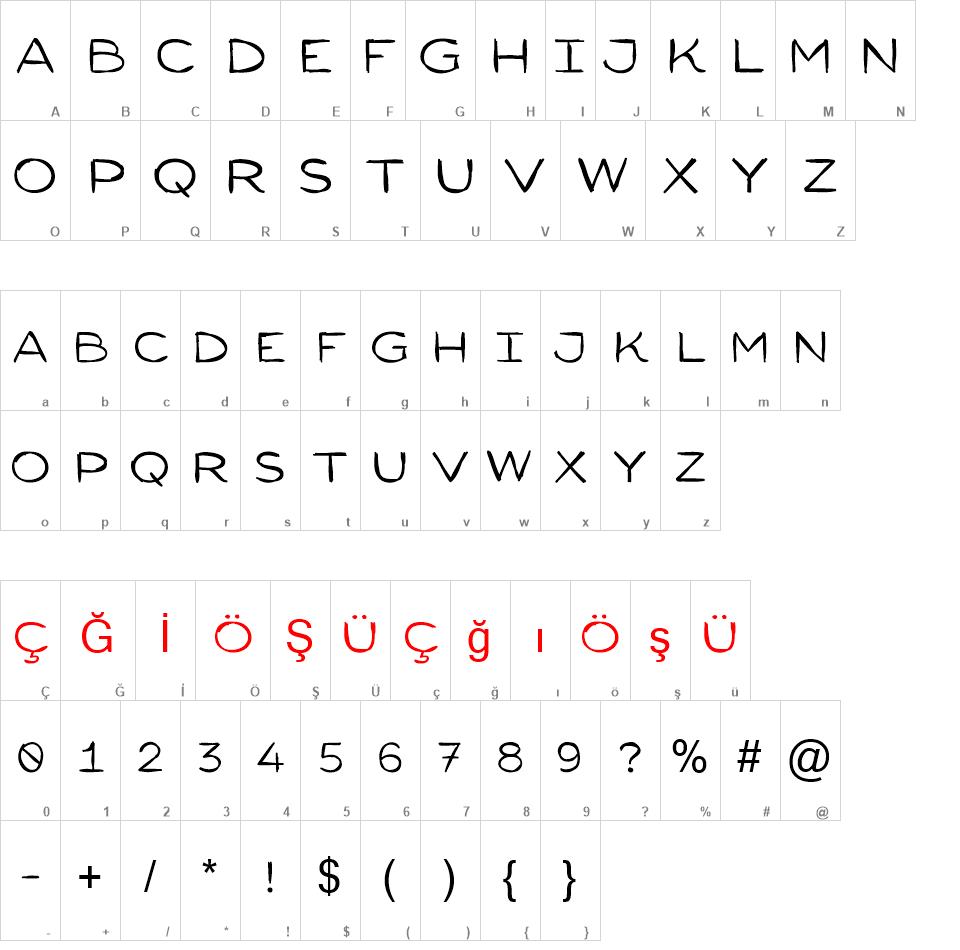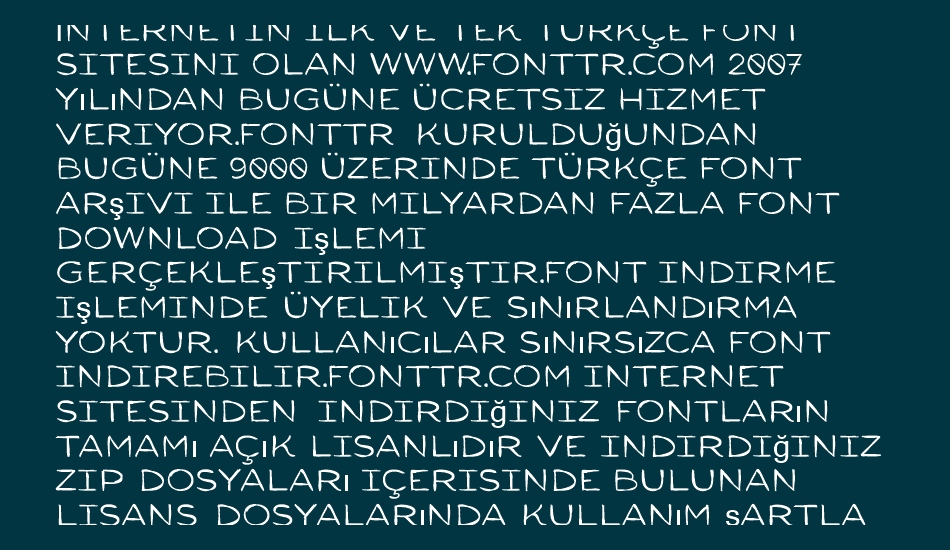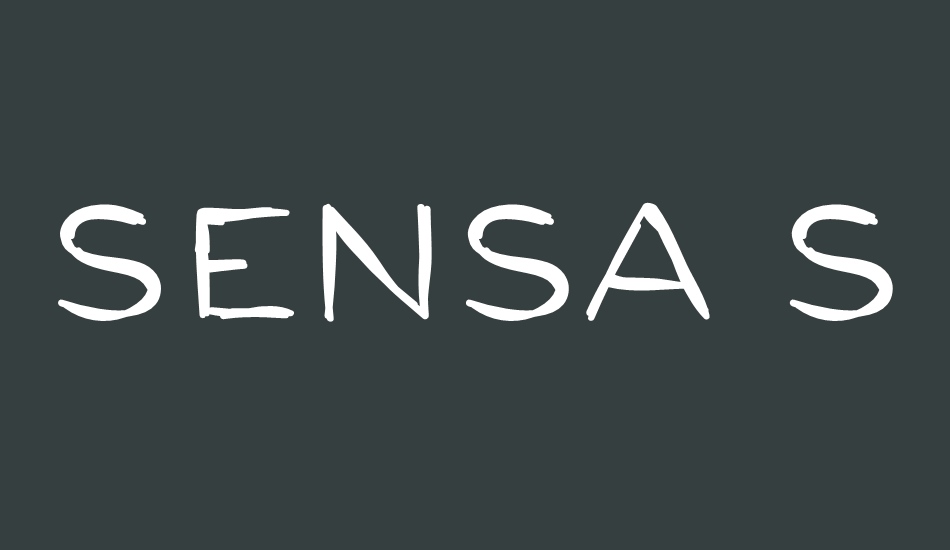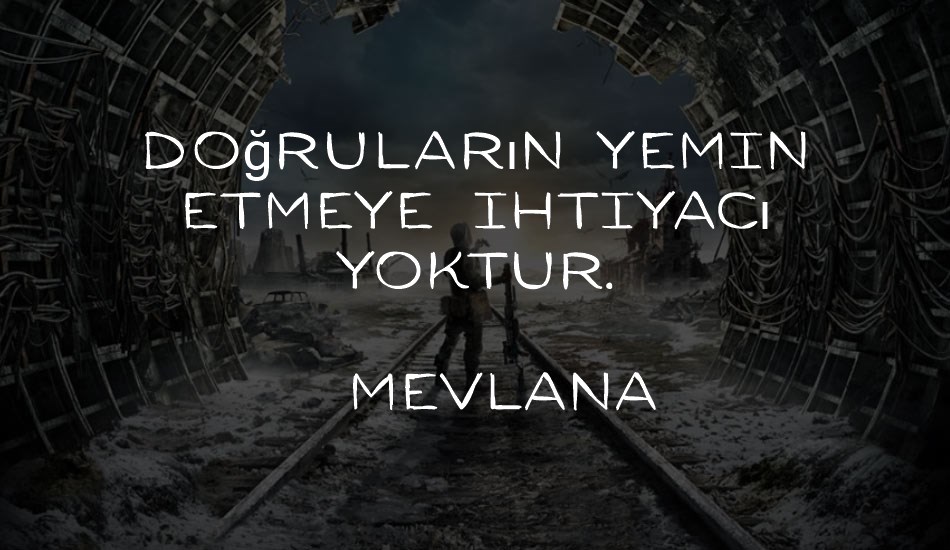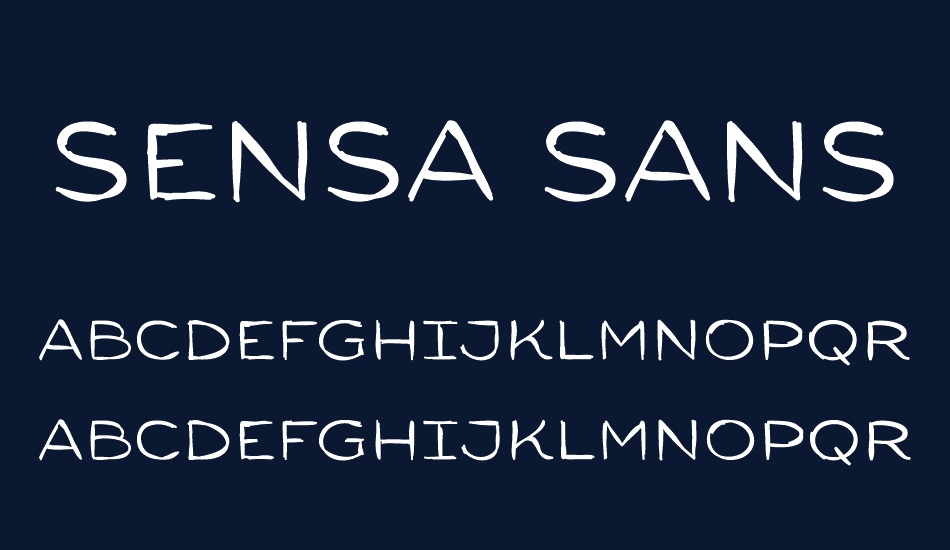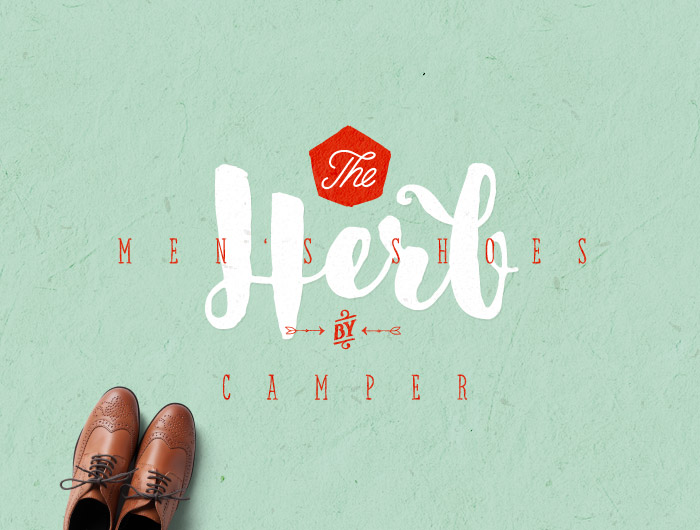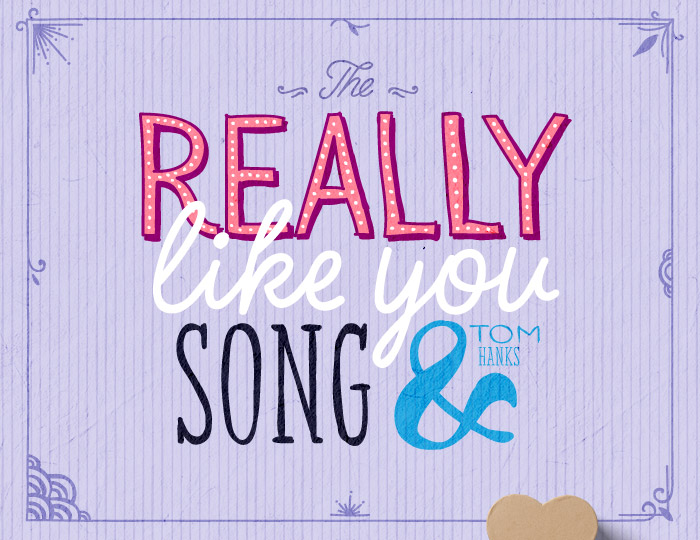
Sensa font
Sensa, 21 yazı tipinden oluşan el yapımı bir font ailesi. Sensa Fırçası, Sensa Kalemi, Sensa Wild, Sensa Sans, Sensa Serif ve Sensa Goodies olmak üzere geniş bir yelpazeye yayılmış görsel güce katkıda bulunan 6 alt aileye ayrılmıştır.
Sınır sadece hayal gücünüzdür. Herhangi bir yazı tipini önde tutan ve geri kalan yazı tiplerini kolaylıkla eşlik edebilir. Olası tüm kombinasyonlarda birlikte çalışmak için, bu paksteki tüm fontlar bu basit fikir düşünülerek oluşturuldu.
Sensa, reklam, paketleme, editöryel ve markalaştırmaya kadar, web ve ekran projelerine kadar her tasarım projesi için geçerlidir. Bir güzellik ve ihale duygusu veya daha fazla erkek ve güçlü iletişim için geniş bir seçiminiz var.
Sensa Sans Demo font